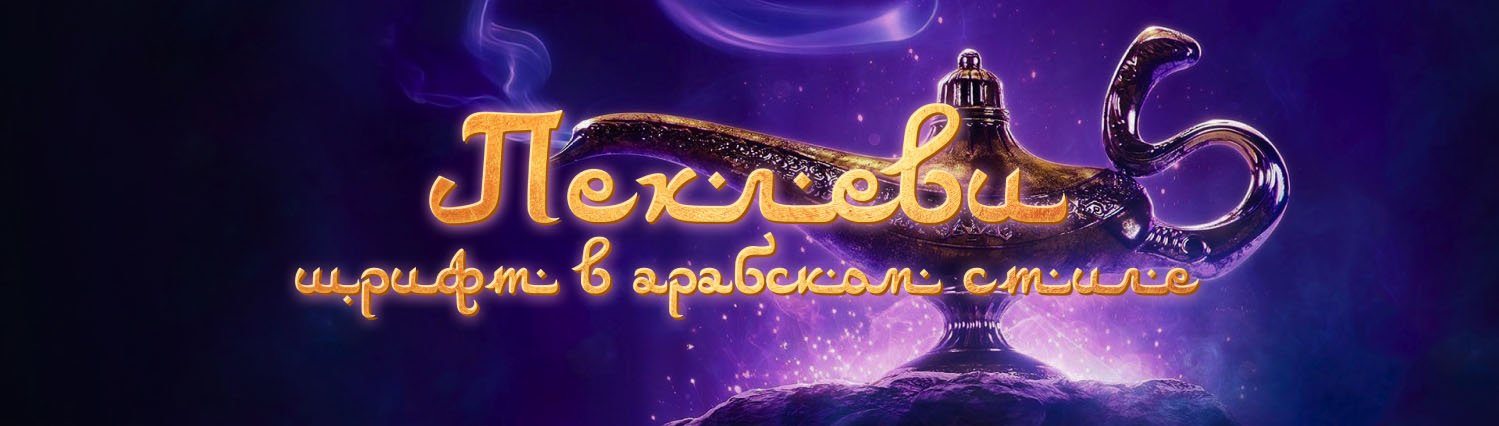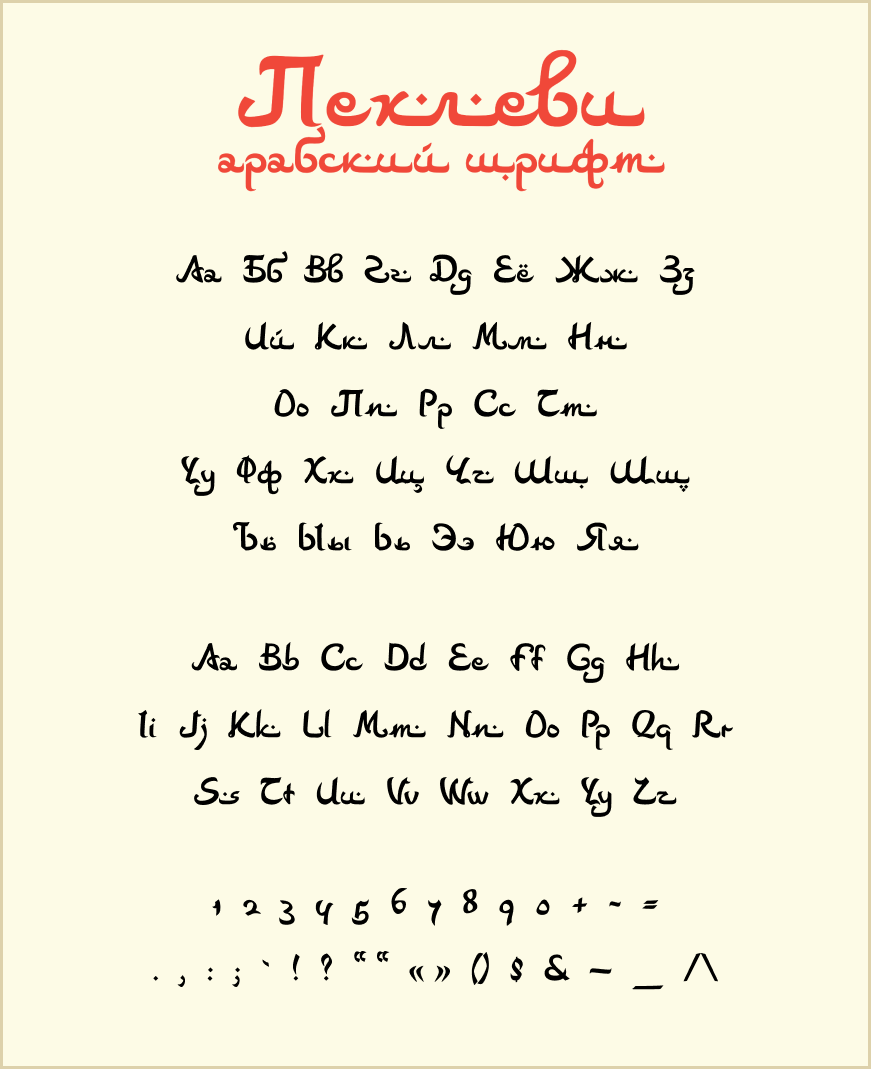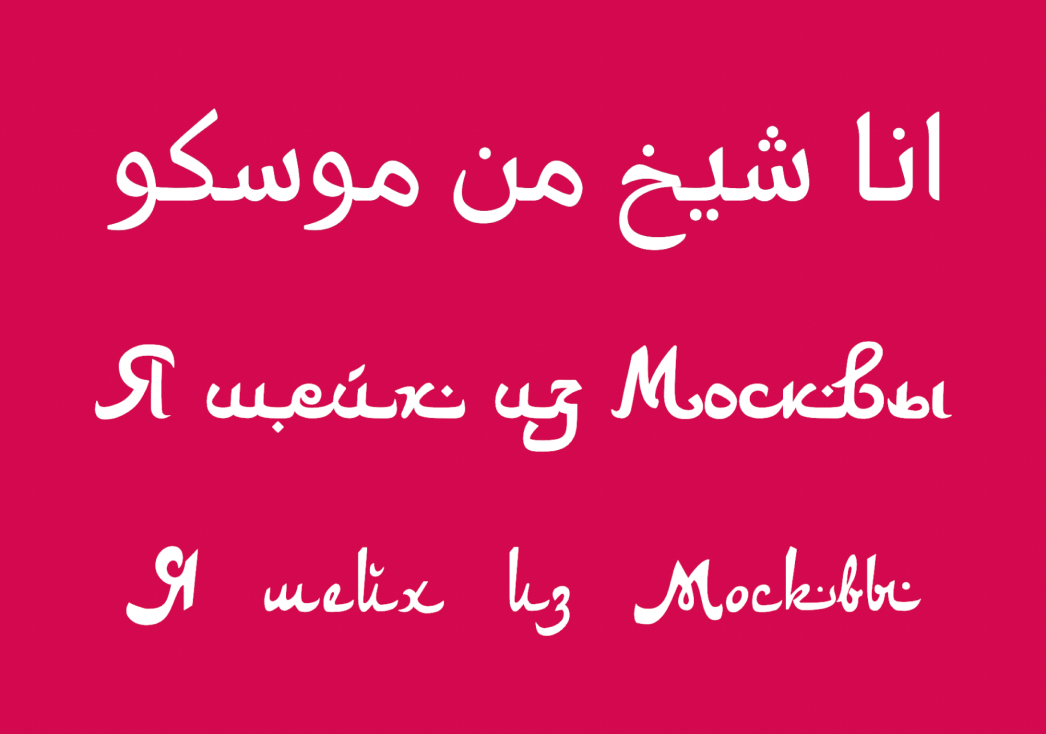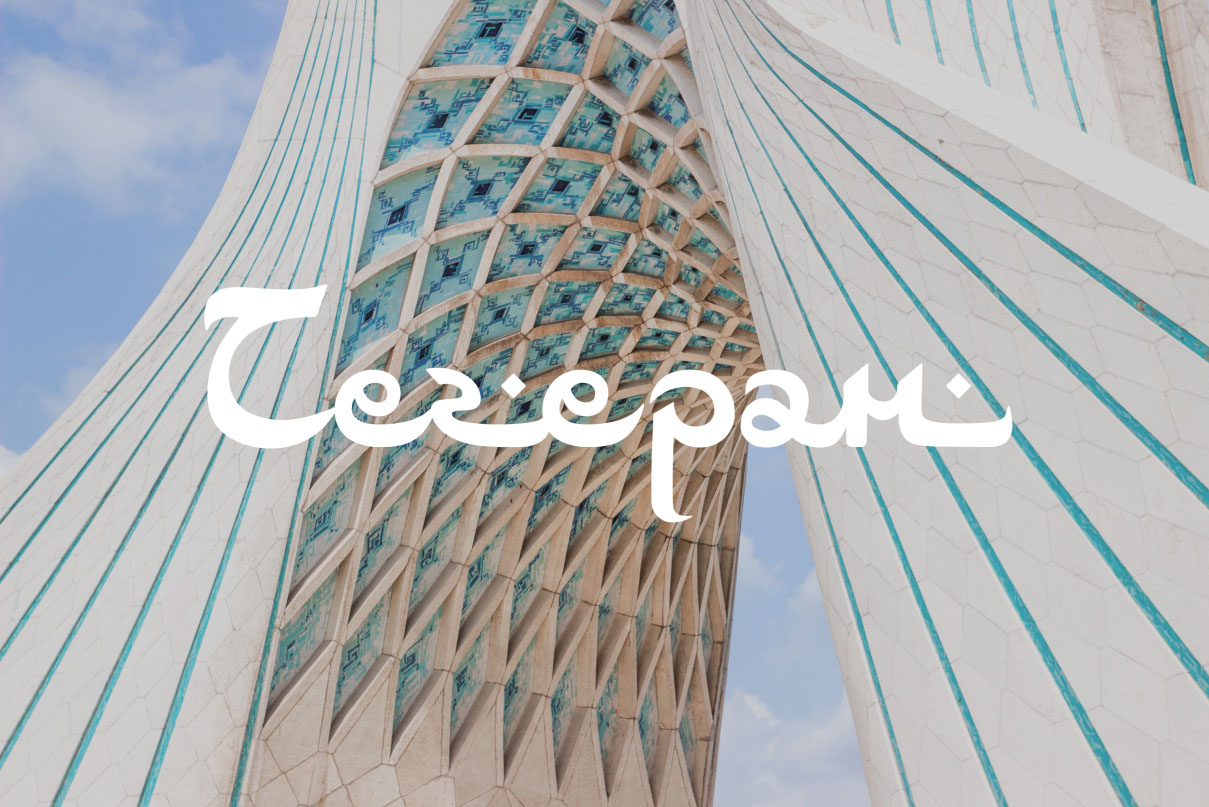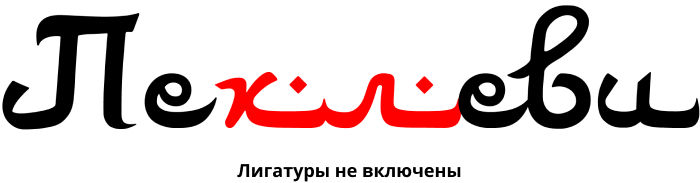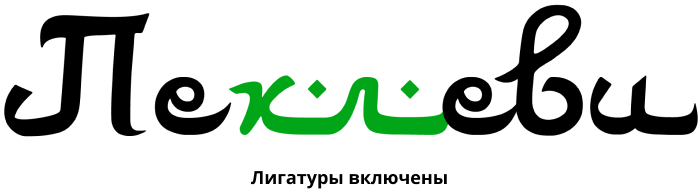
Шрифт в арабском стиле Пехлеви
Пехлеви — русская, кириллическая версия шрифта Abu Dhabi, стилизованного под арабский алфавит. На русском языке есть ровно один шрифт в арабском стиле — DS Arabic. Этот шрифт абсолютно ужасен и подходит только для палаток с шаурмой.
К сожалению, этим шрифтом написаны все «арабские» вывески в России.
Повторить арабскую вязь на другом языке крайне сложно. В арабском языке каждая буква имеет 3 начертания: в начале слова, в середине и в конце одна и та же буква пишется по-разному. Кроме того, арабы лихо закручивают надписи в фигуры, буквально рисуют словами. Поэтому вязь такая красивая и неповторимая.
Шрифт Пехлеви визуально превосходит DS Arabic во всех отношениях и очень похож на настоящий арабский. Взгляните на одну и ту же фразу, записанную на арабском и на русском: шрифтом Пехлеви и шрифтом DS Arabic. Какая больше похожа на оригинал?
Хоть стилизация и не достигает высот арабской каллиграфии, шрифт Пехлеви — это максимум, который можно выжать из русского языка.
Шрифтом Пехлеви написаны заголовки из путешествий по Ирану и Саудовской Аравии.
В шрифте огромное количество лигатур — заранее заготовленных сочетаний букв, благодаря которым симулируется неразрывное написание.
Лигатуры учитывают не все комбинации. Там, где лигатуры не срабатывают, уменьшайте трекинг между буквами вручную. Для ручной калибровки установите курсор между буквами и укажите расстояние -60.